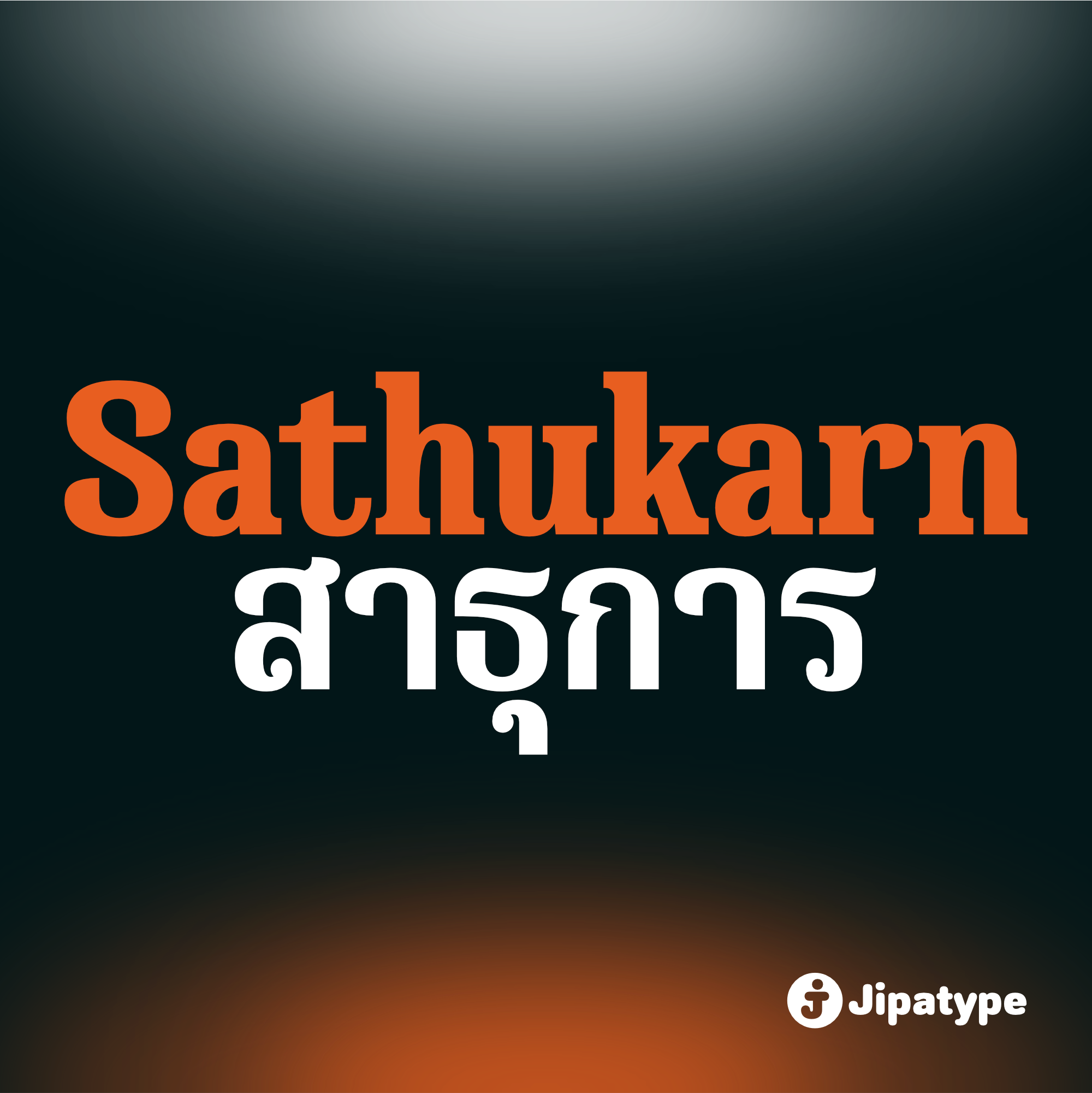
ชื่อฟอนต์ : สาธุการ | Sathukarn
Sathukarn เป็นอักษรแบบสลับแซนเซอริฟสำหรับตัวอักษรละติน และสำหรับอักษรไทยจะเป็นแบบแซนเซอริฟ มีหัวที่ยื่นออกมาในลักษณะม่วนเข้าเป็นวงกลมทึบ มีให้เลือกใช้ถึง 14 สไตล์ รองรับตัวอักษรละตินเซ็ต 1 และอักษรไทย เหมาะสำหรับสิ่งพิมพ์ต่าง ๆ ทั้งออนไลน์และออฟไลน์ ที่เน้นในเรื่องความสงบ ความศรัทธา ไม่ว่าจะอยู่บนป้ายงานบุญต่าง ๆ หรือภาพสวัสดีวันจันทร์ในกลุ่มไลน์ ก็เข้ากันได้ดี